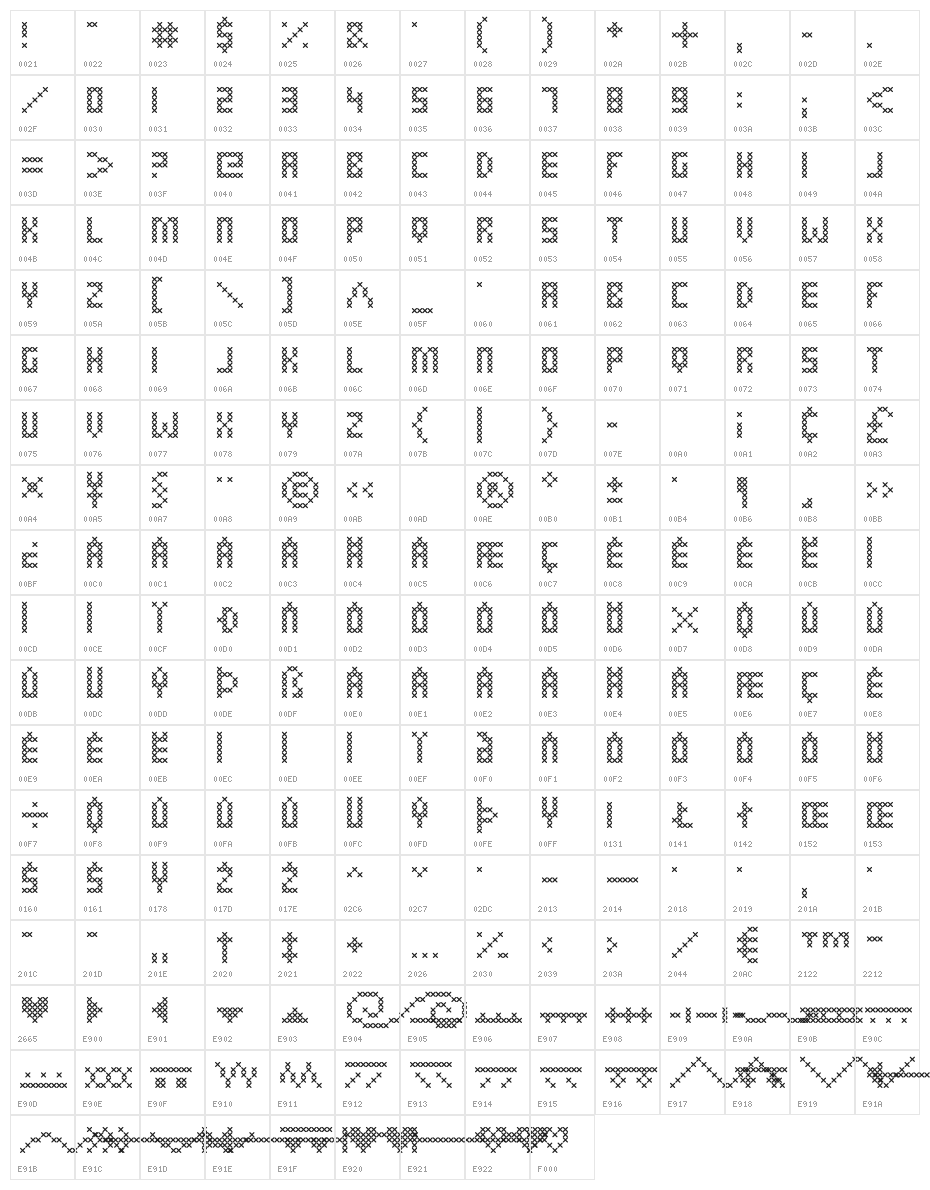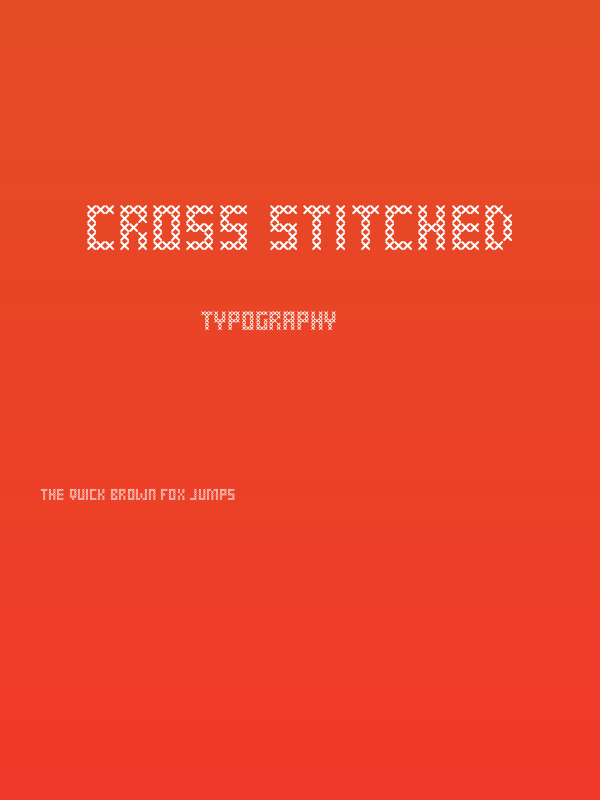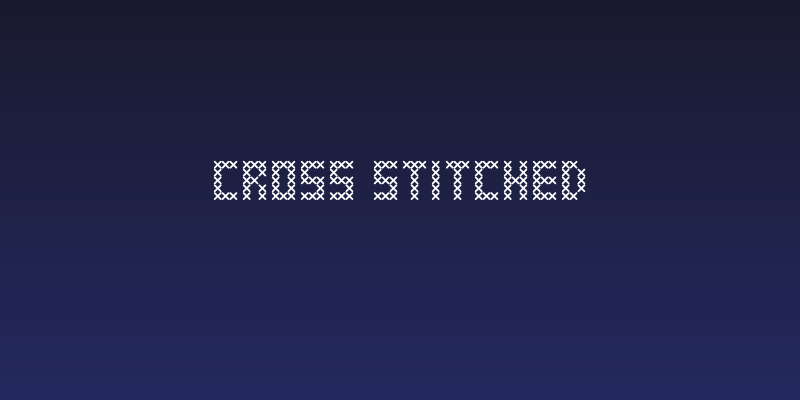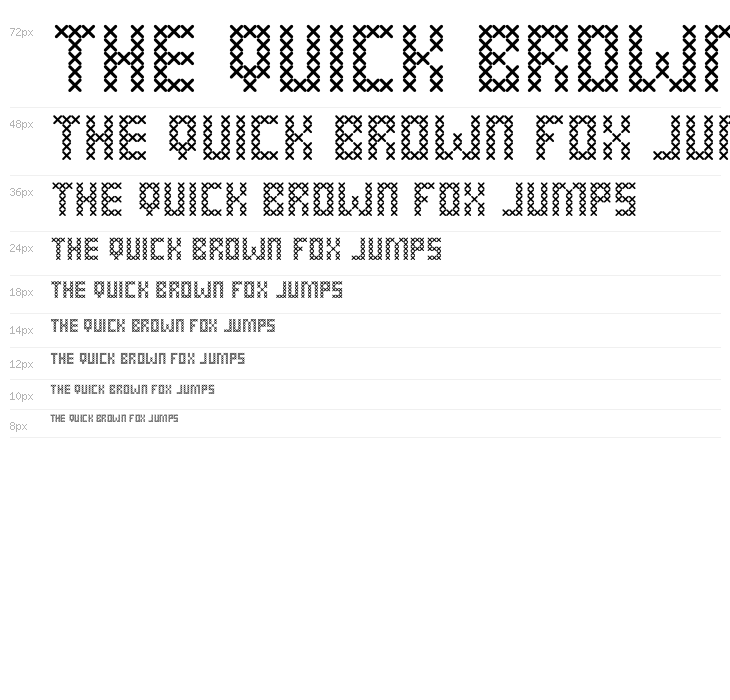
Cross Stitched Font
| Cas d'utilisation | Logos, Headlines, Crafting Projects |
| Projets proposés | Ideal for crafting projects, DIY invitations, handmade product labels, or any design that seeks a vintage or artisanal touch. |